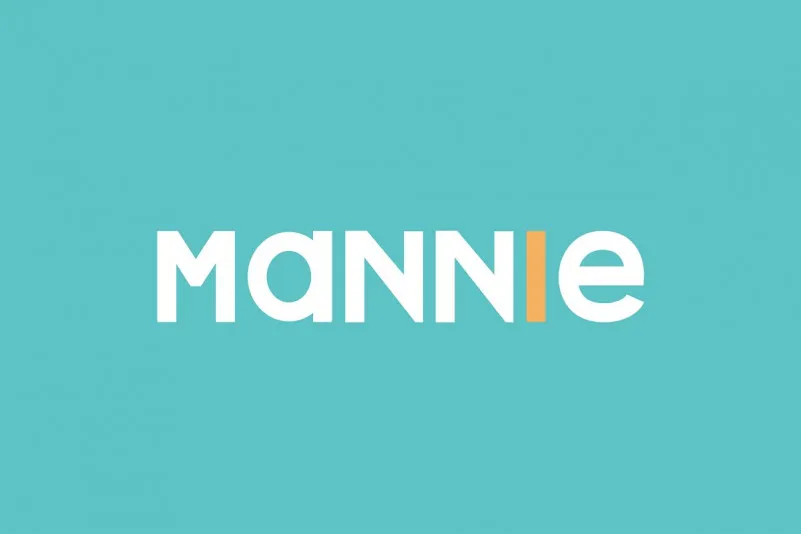
Introduzimos Mannie Font. Desenhado por Cliche Graphique, é uma tipografia premium que você pode adquirir na plataforma Creativemarket. Mas temos a honra de oferecê-la gratuitamente para download hoje. Vamos apresentar Mannie, minha nova fonte sans serif. Maddie é um tipo simples que se destaca graças à sua aparência dinâmica. Com seu aspecto gaseoso, Maddie adicionará uma forte pitada de impacto a qualquer projeto gráfico em que você o use. Esta fonte está disponível gratuitamente para download no Mannie e você pode encontrar mais detalhes sobre ela na sua página oficial. Engane-se se pensar que isso é apenas um nome: com seu aspecto leve e efervescente, Maddie traz uma nova emoção à sua tipografia.